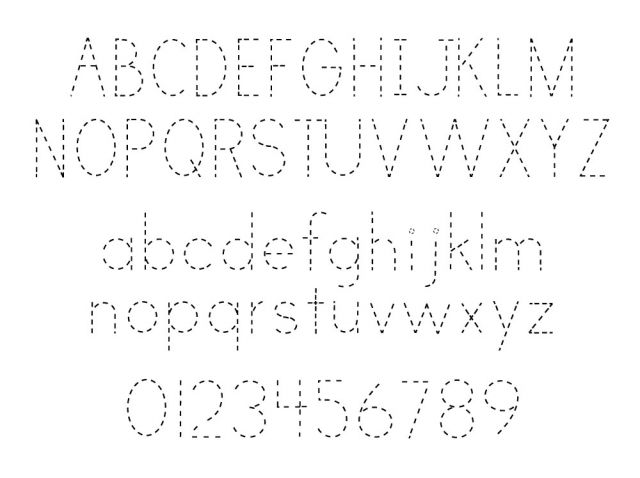
Как самостоятельно создать «Прописи» для обучающихся
В последнее время особенно актуальной в методике преподавания русского языка является проблема обучения первоклассников каллиграфически правильному письму, так как все чаще у обучающихся возникают трудности при овладении техникой письма, которые имеют разные причины: и физиологические, и психологические, и педагогические.
Первый этап — подготовка руки к письму. В этом помогут упражнения на развитие мелкой моторики, лепка, рисование, оригами.
Второй этап — штрихование и раскрашивание. Следите при этом, чтобы ребенок правильно захватывал пишущий инструмент (ручку или карандаш).
Третий этап — работа в прописях.
Четвертый этап — написание прописных букв.
В первую очередь педагогу следует обратить внимание на “Прописи”, которые являются основными помощниками учителю и детям. Они составляются в соответствии с букварем и содержат образцы букв.
“Прописи” облегчают работу учителя, а для
Почерк – устойчивая манера письма, зафиксированная в рукописи система привычных движений, в основе формирования которой лежит письменнодвигательный навык.
Обучение письму — это в первую очередь выработка навыка графического. Как и всякий навык, он формируется в результате обучения, в результате формирования умений и на их основе выполнения ряда упражнений.
Особенности графического навыка в том, что это, с одной стороны, двигательный навык, то есть такое действие, которое опирается, на первый взгляд, лишь на мускульные усилия. С другой же стороны, в процессе письма осуществляется перевод осмысленных единиц речи в графические знаки (перекодировка). Что придает письму характер сознательной деятельности. Эта сторона письма как специфической человеческой деятельности и составляет главное в навыке письма.
Но ни для кого не секрет, что время на обучение ребенка правильному каллиграфическому письму в первом классе сведено к минимуму.
Следовательно, плохо прописанные элементы и буквы на начальном этапе формирования письма могут привести к трудностям в дальнейшем.
Закрепить навык письма, выработать автоматическое правильное и, что самое главное, понятное написание письменных букв помогают дополнительные занятия с прописями.
1. Написание прямых наклонных линий с соблюдением точных интервалов и их параллельности.
2. Деление наклонной линии и рабочей строки на 2 и 3 части по вертикали с целью подготовки к правильному выполнению соединений элементов букв и букв в слове (включение определенного математического расчета в написание букв, слов).
3. Выполнение закругления на нижней линии рабочей строки как связующего элемента между двумя разнонаправленными линиями.
4. Письмо крючковой линии до середины строки. (Крючковая линия вместе с прямой наклонной и закруглением обычно называется крючком.)
5. Письмо «секрета», т. е. прямой линии, которая продолжает крючковую линию от середины строки до верхней ее линеечки, соединяя конец крючка с верхней линеечкой рабочей строки («секрет» пишется параллельно прямой наклонной линии.
6. Письмо вниз по «секрету» до нижней линии строки, т.е. написание второй наклонной линии («прячем «секрет»).
7. Завершение написания второго крючка (второе закругление и вторая крючковая линия).
Чтобы грамотно работать с прописями, надо помнить несколько правил:
- Для начала прописывать все элементы, из которых состоят буквы.
- Перед написанием буквы, проанализировать все ее элементы. Замечено, что скорость в освоении новой буквы значительно увеличивается, когда ученик видит, что подобные элементы он встречал ранее и уже умеет их писать.
- Показать направление движения при письме. В формате индивидуальных занятий можно попросить ребенка пальчиком провести по букве, закрепляя нужное направление движения при письме.
- Соблюдать речевую формулу. Речевая формула — это план ответа, опора для самоконтроля, возможность упорядочить свои действия и речь.
Сейчас в помощь учителям и родителям созданы он-лайн сервисы.
- Генератор заданий “Прописи”.
Этот вариант прост в использовании (см. рис.)
Заполняем все пункты и получаем вот такой лист с заданием, который конвертируется в формат PDF:
Лист Прописей2. Есть еще один он-лайн генератор, который поможет создать дополнительные материалы под потребности обучающегося.
Шаг 1. Чтобы составить прописи, выберите на панели нужные вам функции.
Шаг 2. Вид страницы: в косую линию, в узкую линию, в широкую линию.
Шаг 3. Вид шрифта: пунктирный, сплошной серый, сплошной черный.
Если необходимо обвести буквы, то выберете пунктирный шрифт или сплошной серый.
Шаг 4. Положение страницы: книжное, альбомное.
В отдельной строке напишите задание.
Шаг 5. Далее заполните форму текстом на свое усмотрение.
Это могут быть отдельные элементы, буквы, слоги, слова.
Вы можете создать прописи не только на кириллице. Используя латинскую раскладку клавиатуры, вы можете сгенерировать прописи по английскому и немецкому языку.